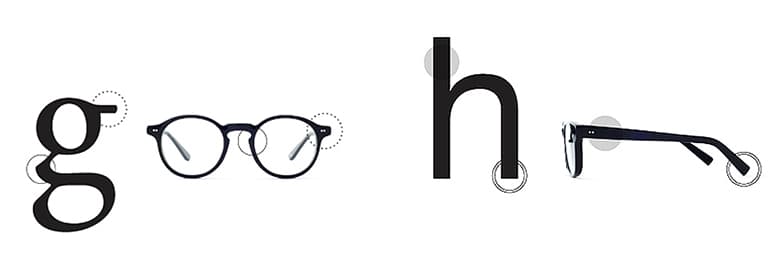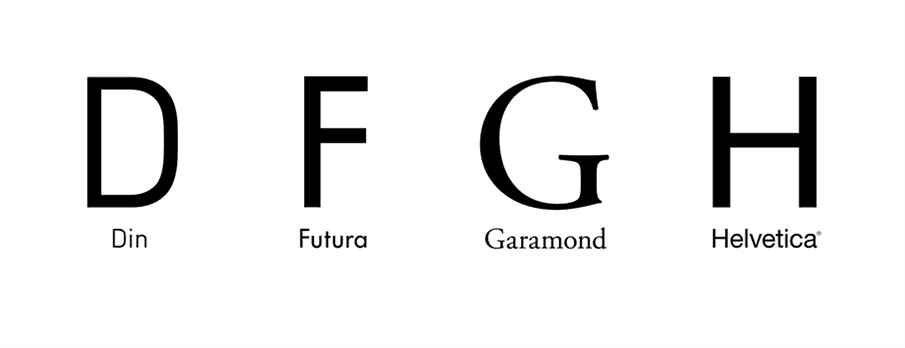
フォントから生まれた眼鏡「TYPE」
街で見かける看板や雑誌のタイトル、商品のパッケージなど、私たちの身の回りにはフォントが溢れています。
フォント×眼鏡
昨年話題となった、こんな面白いプロダクトをご存知でしょうか。
フォントの個性を眼鏡のデザインに落とし込んだブランド「TYPE」です。
フォント×眼鏡
現在のラインナップは、Helvetica、Garamond、DIN、FUTURAの4種類。書体(typeface)に忠実に、セリフ(文字の端に付けられる飾り)の有り無しやカーブ具合を再現しているだけでなく、Light、Regular、Boldなどフレームの太さも選べます。この「TYPE」は何個注文しても5日以内であれば返品可能という、通販ながら家で合うものを試着できる独自のシステムが話題のメガネ・サングラス通販サイト「Oh My Glasses」が、NIKEのプロモーションを手がけていることで有名な、アメリカ・ポートランドに本社を置くクリエイティブエージェンシーの東京支社である「Wieden+Kennedy Tokyo」とともに立ち上げたブランドです。
共通項を見つける
フォントと眼鏡、全く関係のないように見えるこの二つですが、実は微妙な太さ、形の違いが人に与える印象を変える、という共通項があります。
全く違うもの同士の共通項を見つけ、組み合わせて新しい価値を生み出すという発想は、デザインにおいても大切ですよね。
自分とほかの人が持っているフォントに対する印象がそれぞれ違っていたり、そのフォントを元にした眼鏡から受ける印象がまた違ったり、色んな感じ方があって見ているだけでも楽しくなります。
今後どんなフォントを元にした商品が出てくるのかが楽しみですね。